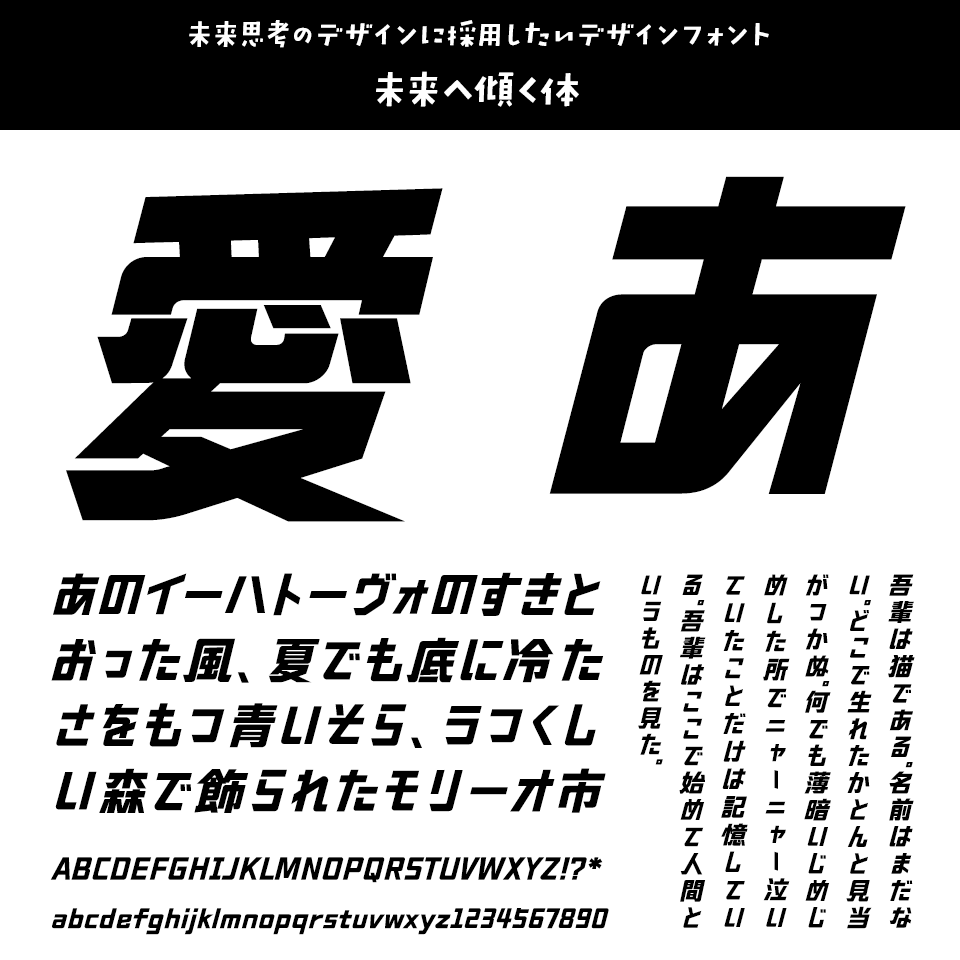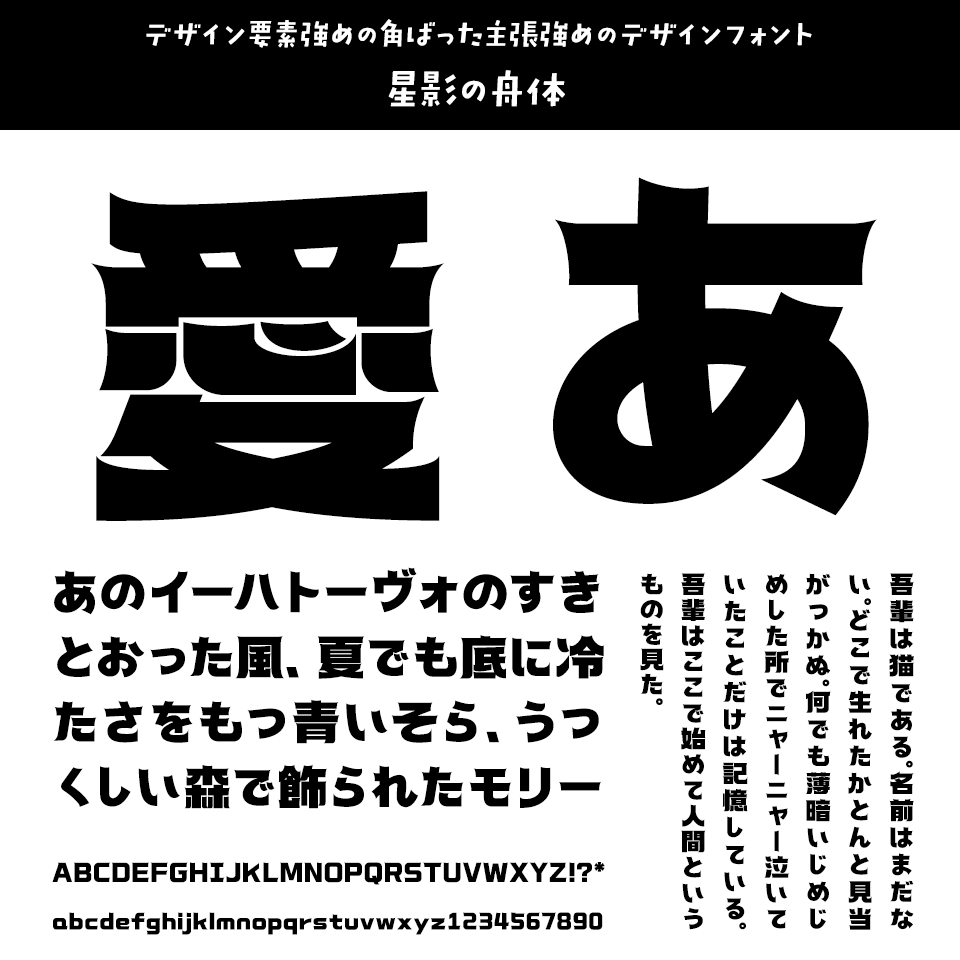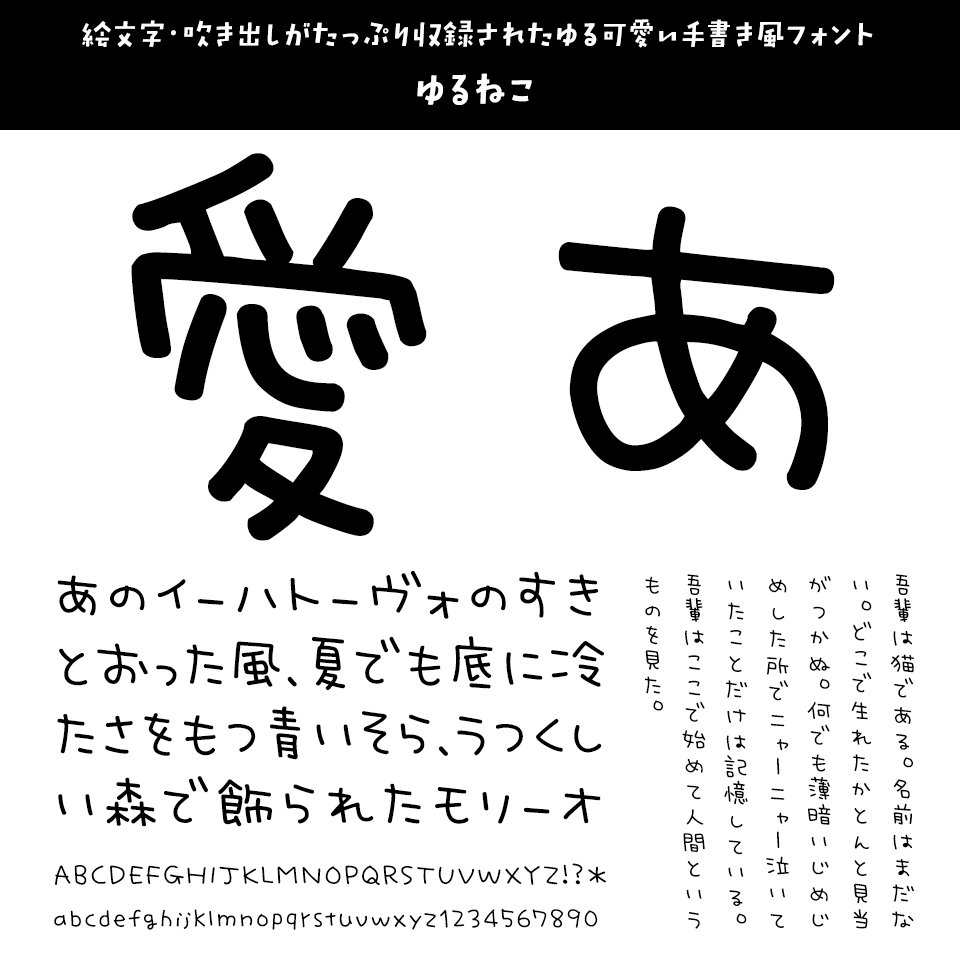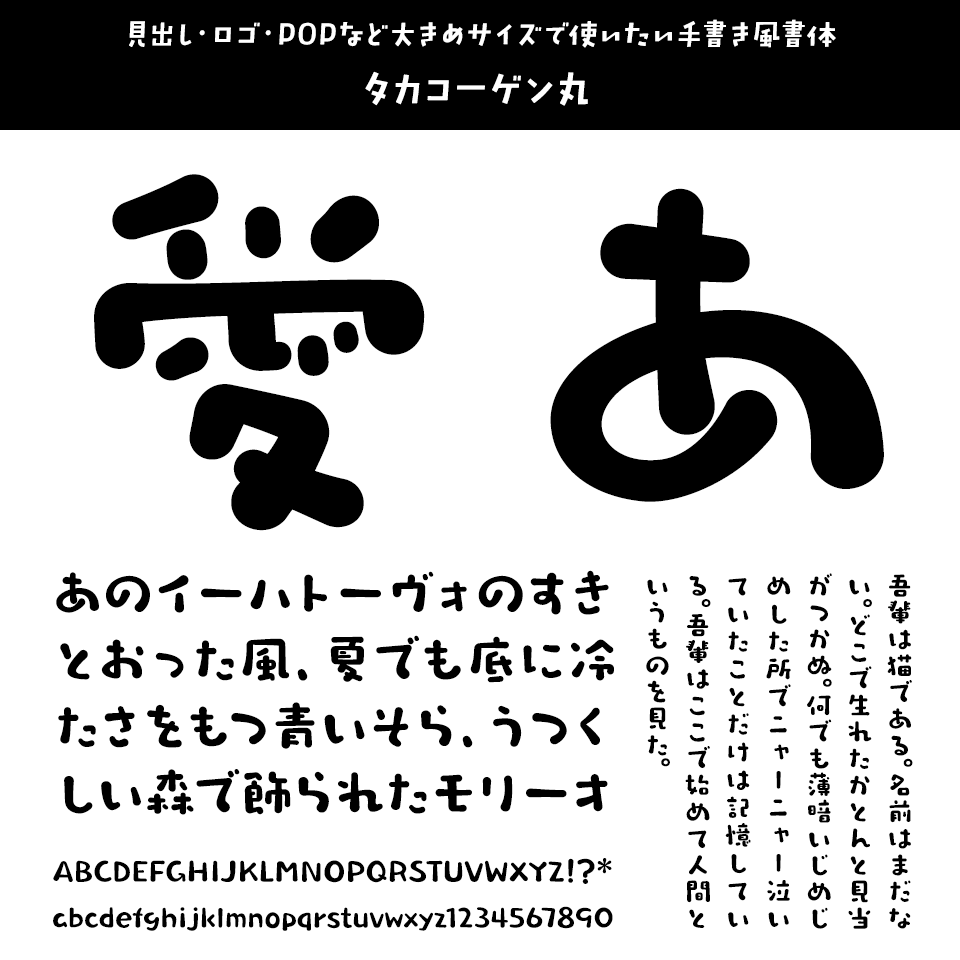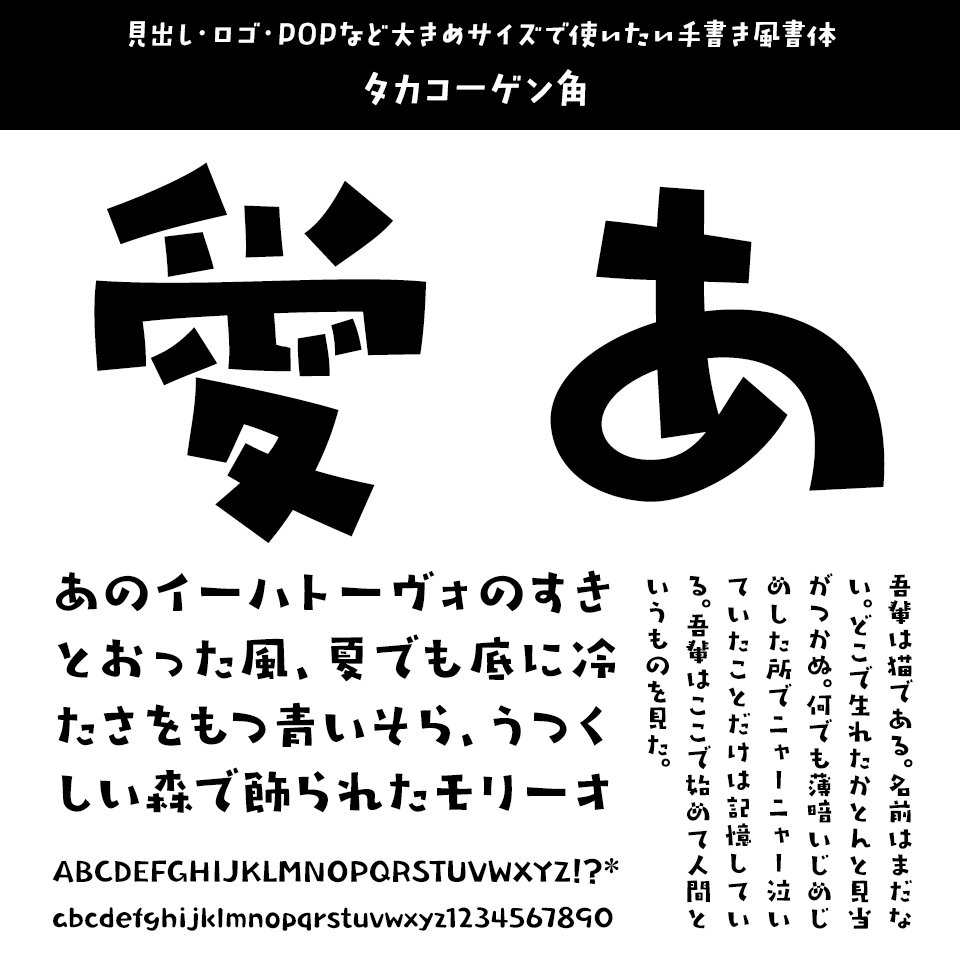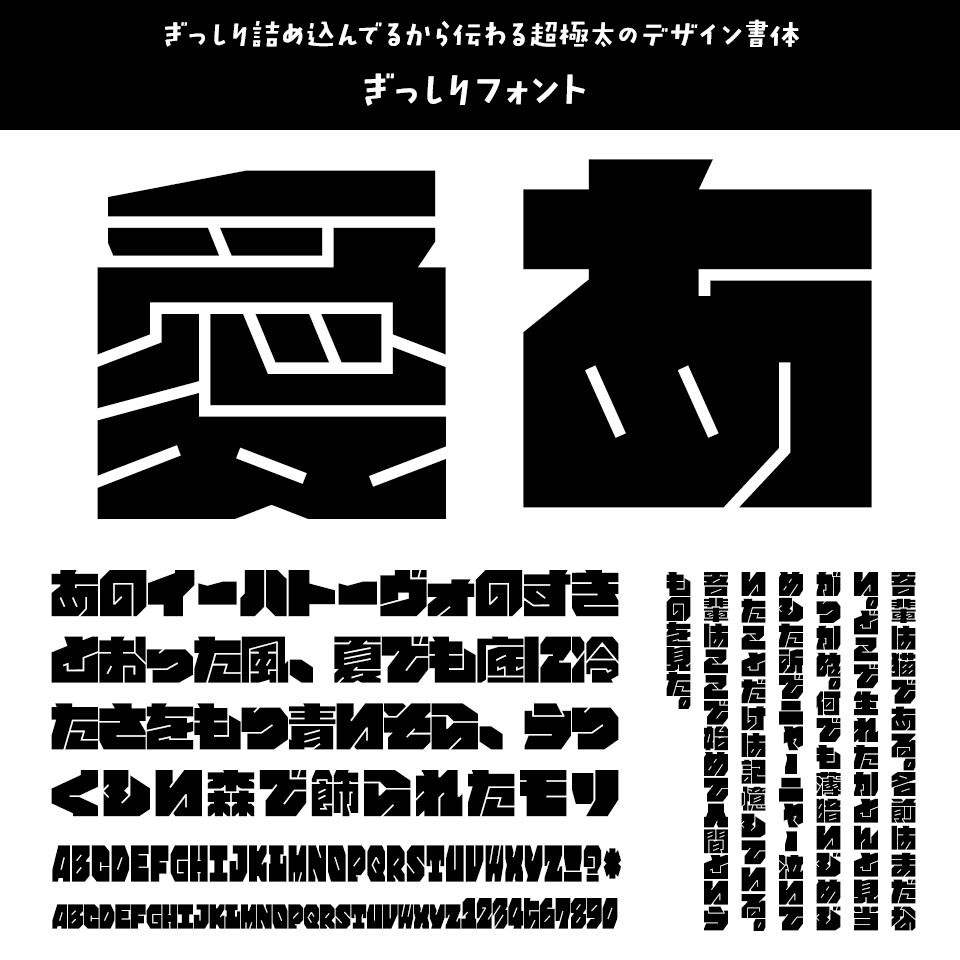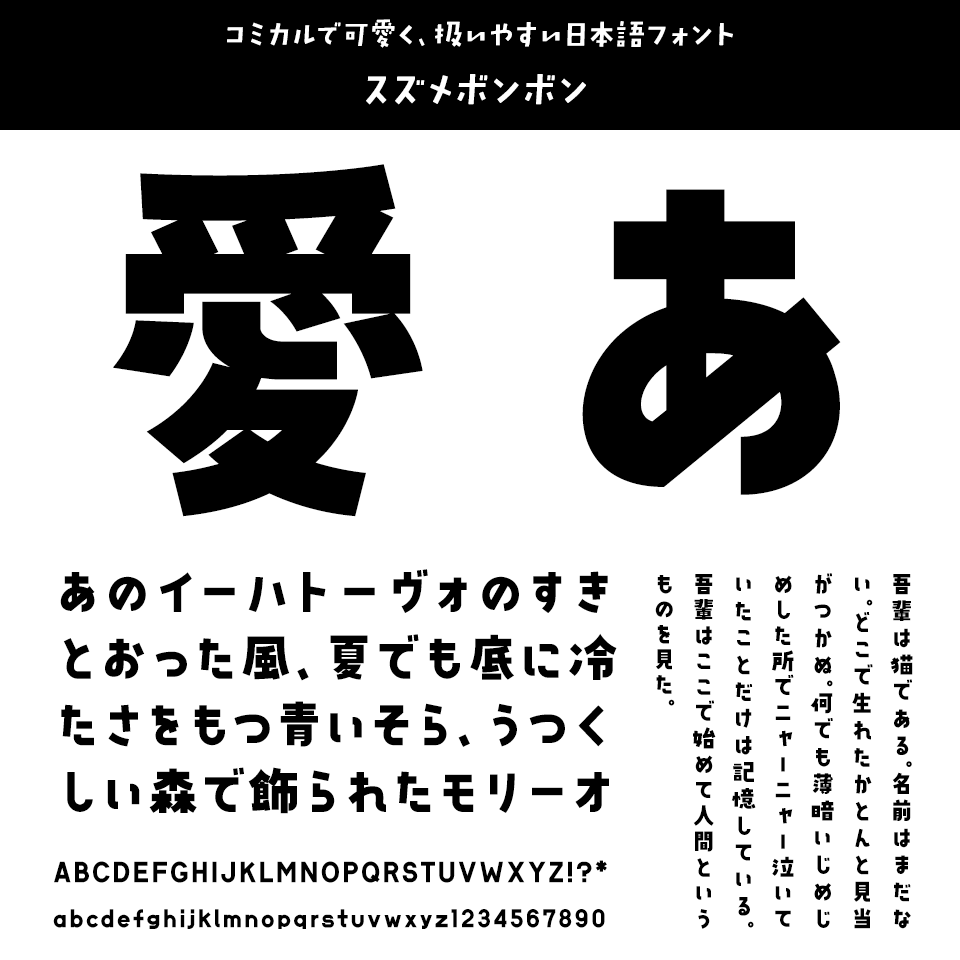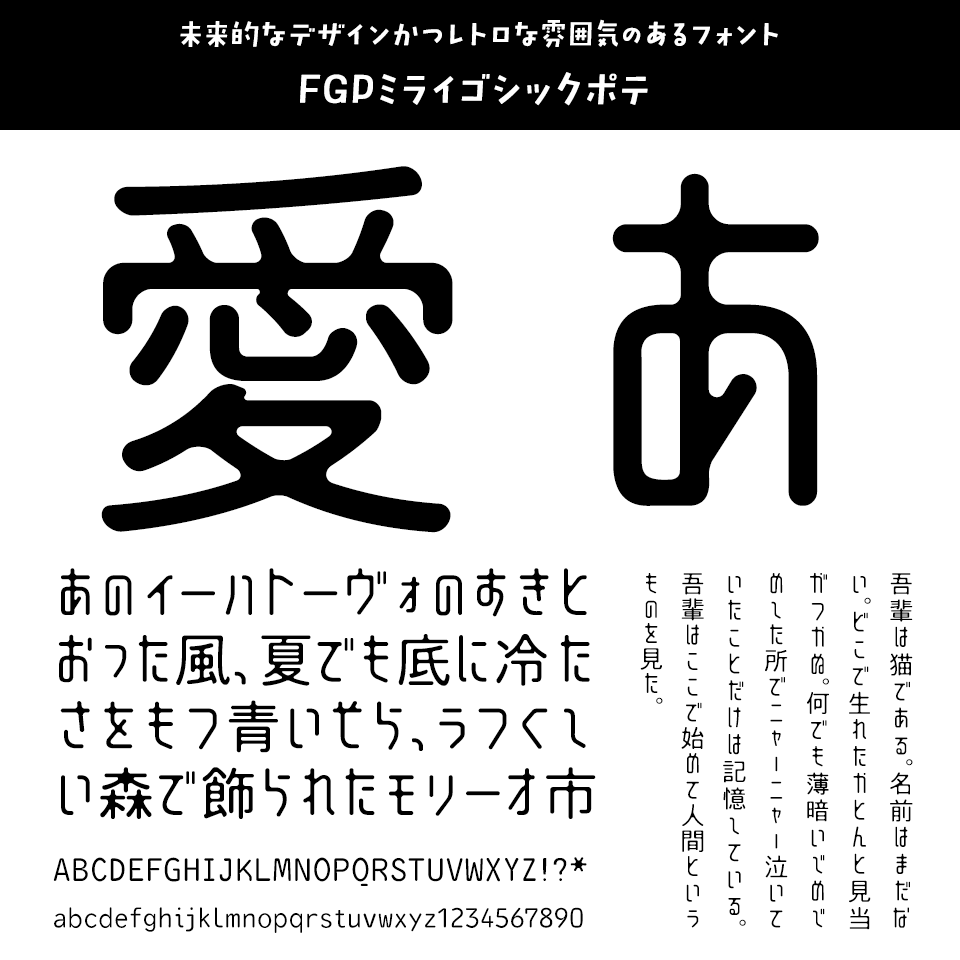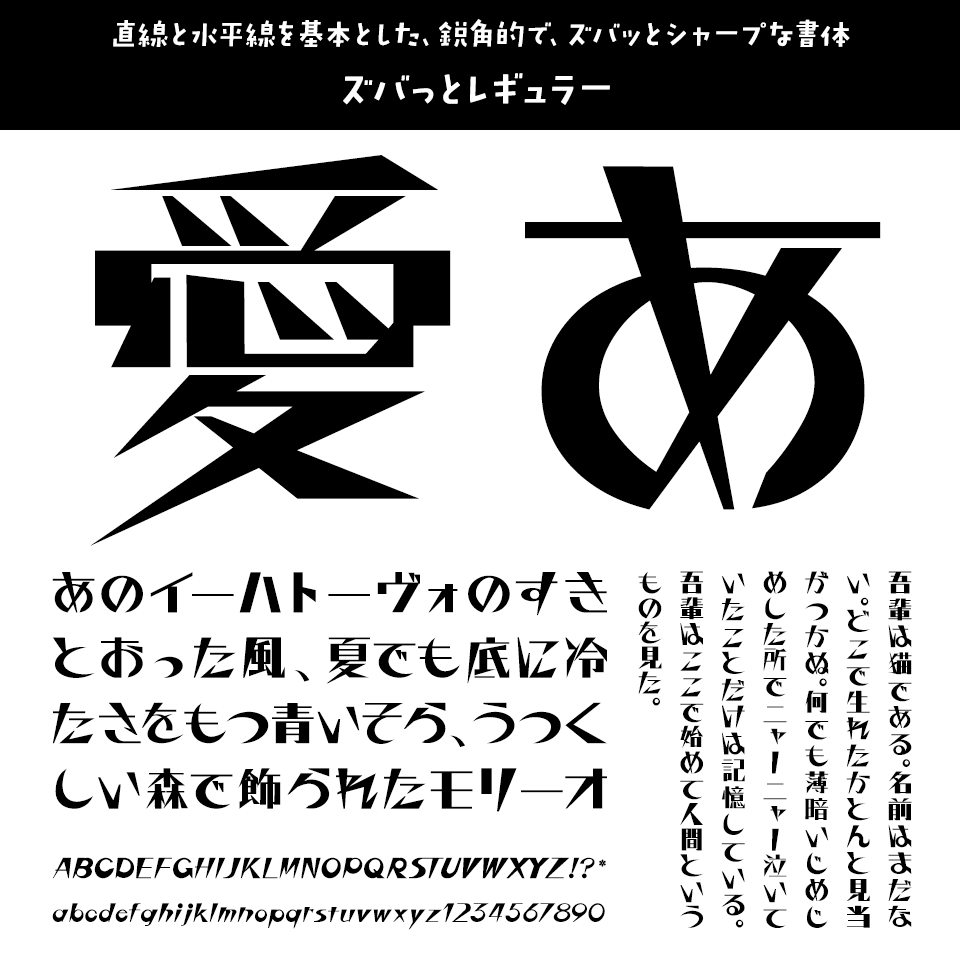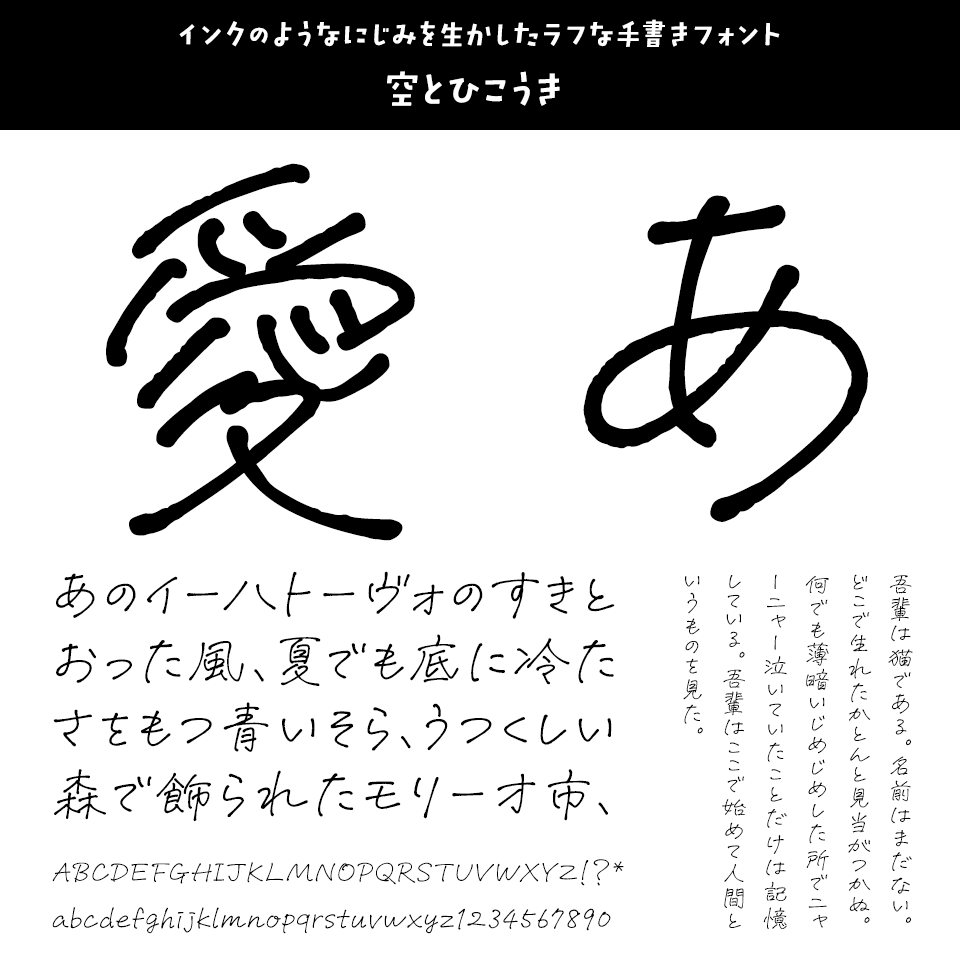
「今、買っておきたいフォント」 未来へ傾く体
未来思考のデザインに採用したいデザインフォント
「今、買っておきたいフォント」 未来へ傾く体
前傾した骨格と鋭いエッジが生み出す、スピード感と力強さが特徴のフォントです。引き締まった文字形が動きを強調します。
「今、買っておきたいフォント」 星影の舟体
デザイン要素強めの角ばった主張強めのデザインフォント
「今、買っておきたいフォント」 星影の舟体
極太の筆画とやわらかなコーナーにより、力強さと親しみやすさをあわせ持つフォントです。ふくらみのある字形が存在感を生み、丸み処理がさをやわらげて読みやすさを高めます。
「今、買っておきたいフォント」 ゆるねこ
絵文字・吹き出しがたっぷり収録されたゆる可愛い手書き風フォント
「今、買っておきたいフォント」 ゆるねこ
ゆる可愛い手書き風フォントで、しなやかな線と親しみある造形が特徴。通常版に加えて絵文字・吹き出し入りの「ゆるねこ*emoji」も収録されており、POPやSNS投稿などで可愛く楽しく使えます。
「今、買っておきたいフォント」 ねこのけフォント 冬
可愛い系には必須の手書き丸文字フォント
「今、買っておきたいフォント」 ねこのけフォント 冬
冬の寒さに備えて毛を蓄えた猫のふっくらふわふわな毛並みをイメージしたふんわり丸文字の手書き日本語フォントです。見出しだけではなく、本文や縦書きでもふんわり読みやすくそして可愛らしく使えます。
「今、買っておきたいフォント」 タカコーゲン丸
見出し・ロゴ・POPなど大きめサイズで使いたい手書き風書体
「今、買っておきたいフォント」 タカコーゲン丸
先端と末端を丸めることでフレンドリーさと安心感をプラス。カフェやキッズ、雑貨など“やさしい世界観”に自然と馴染み、初見ユーザーにもやわらかく届きます。
「今、買っておきたいフォント」 タカコーゲン角
見出し・ロゴ・POPなど大きめサイズで使いたい手書き風書体
「今、買っておきたいフォント」 タカコーゲン角
郭を整えることで読みのエッジを立て、情報整理や屋外掲示でも視認性よく仕上がります。清潔感を求めるポスターや店頭サイン、Webの小見出しにも好相性です。
「今、買っておきたいフォント」 ぎっしりフォント
ぎっしり詰め込んでるから伝わる超極太のデザイン書体
「今、買っておきたいフォント」 ぎっしりフォント
文字の線一本一本が限界まで太く、文字枠いっぱいに詰め込まれた「ぎっしりフォント」。東急プラザ蒲田の「カマタしようぜ!」にも採用された大注目フォントです。
「今、買っておきたいフォント」 スズメボンボン
コミカルで可愛く、扱いやすい日本語フォント
「今、買っておきたいフォント」 スズメボンボン
ヤマナカデザインワークスによる和文デザイン書体です。ひらがな・カタカナ・英数字・記号・漢字を幅広く収録しており、タイトルやロゴ、ポスター、SNSグラフィックなど、さまざまなクリエイティブに柔軟に対応します。
「今、買っておきたいフォント」 FGPミライゴシックポテ
未来的なデザインかつレトロな雰囲気のあるフォント
「今、買っておきたいフォント」 FGPミライゴシックポテ
スッキリとした印象の「FGPミライゴシック」に、角が丸くておしゃれな形の「FGPミライゴシックポテ」。右肩上がりでより未来感が増した「FGPミライゴシックポテ斜め」の3書体を収録しています。
「今、買っておきたいフォント」 ズバッとレギュラー
直線と水平線を基本とした、鋭角的で、ズバッとシャープな書体
「今、買っておきたいフォント」 ズバッとレギュラー
鋭角的でエッジの効いた文字デザインが視線を強く引きつけ、太さと直線が際立つモダンな印象。タイトルや見出しなどで力強い存在感を発揮します。
「今、買っておきたいフォント」 空とひこうき
インクのようなにじみを生かしたラフな手書きフォント
「今、買っておきたいフォント」 空とひこうき
花とちょうちょ、パンダベーカリーなど、SNSや商品パッケージ、動画のテロップなど、幅広い場面で見かける機会が多い鈴木メモさんのフォント。今回ご紹介する書体は、フチのにじみや先端のインク溜まり、勢いのある線の強弱などを生かしたリアル感のある手書きフォントとなっております!
「今、買っておきたいフォント」 Fancy Star Script
可愛さMAXのレトロポップ系筆記体フォント
「今、買っておきたいフォント」 Fancy Star Script
Xに投稿するたび多くのいいね!をいただく、satsuyakoさんの筆記体フォント。少しレトロでポップな雰囲気と、星のあしらいが可愛すぎるフォントです。